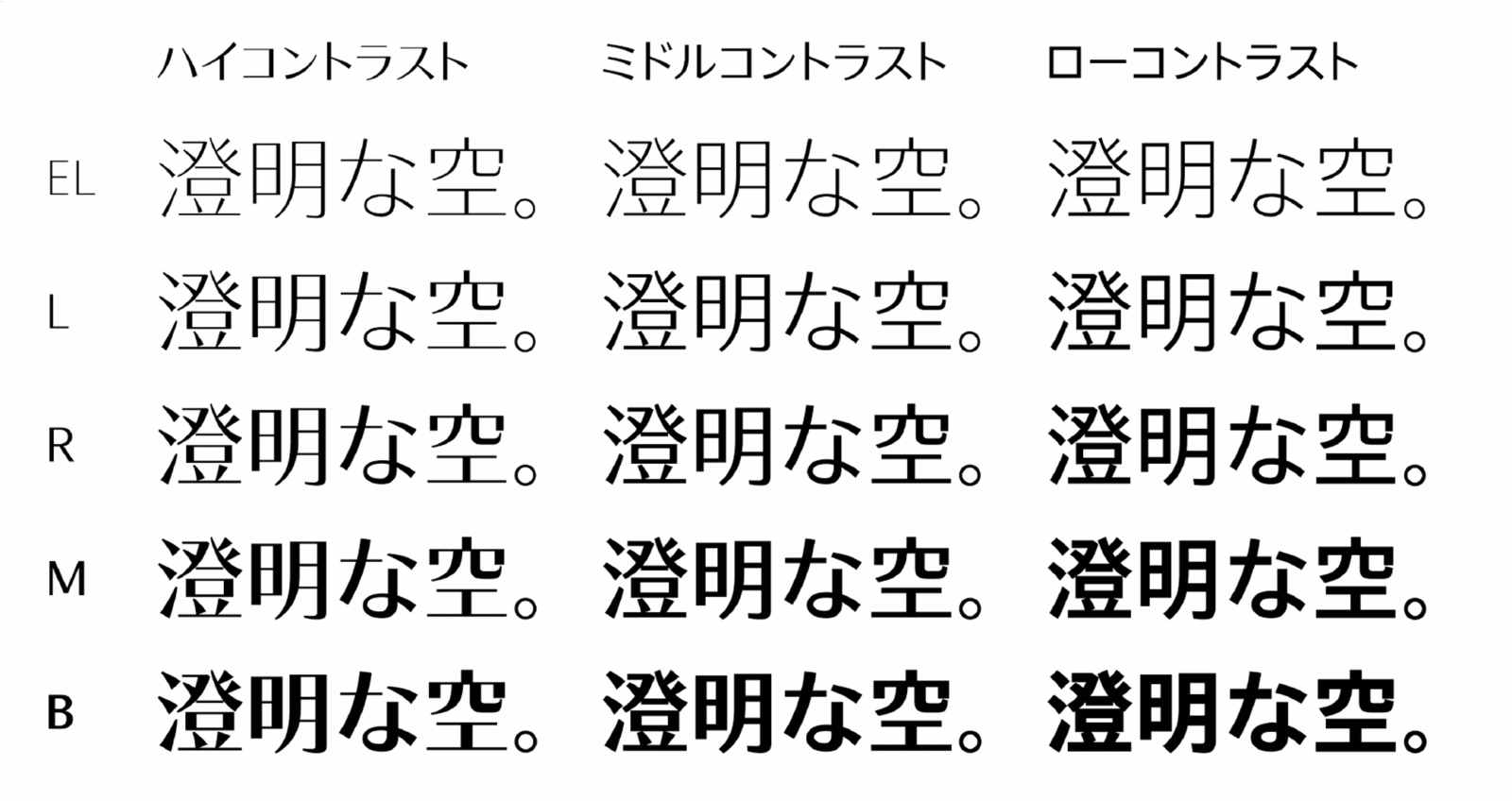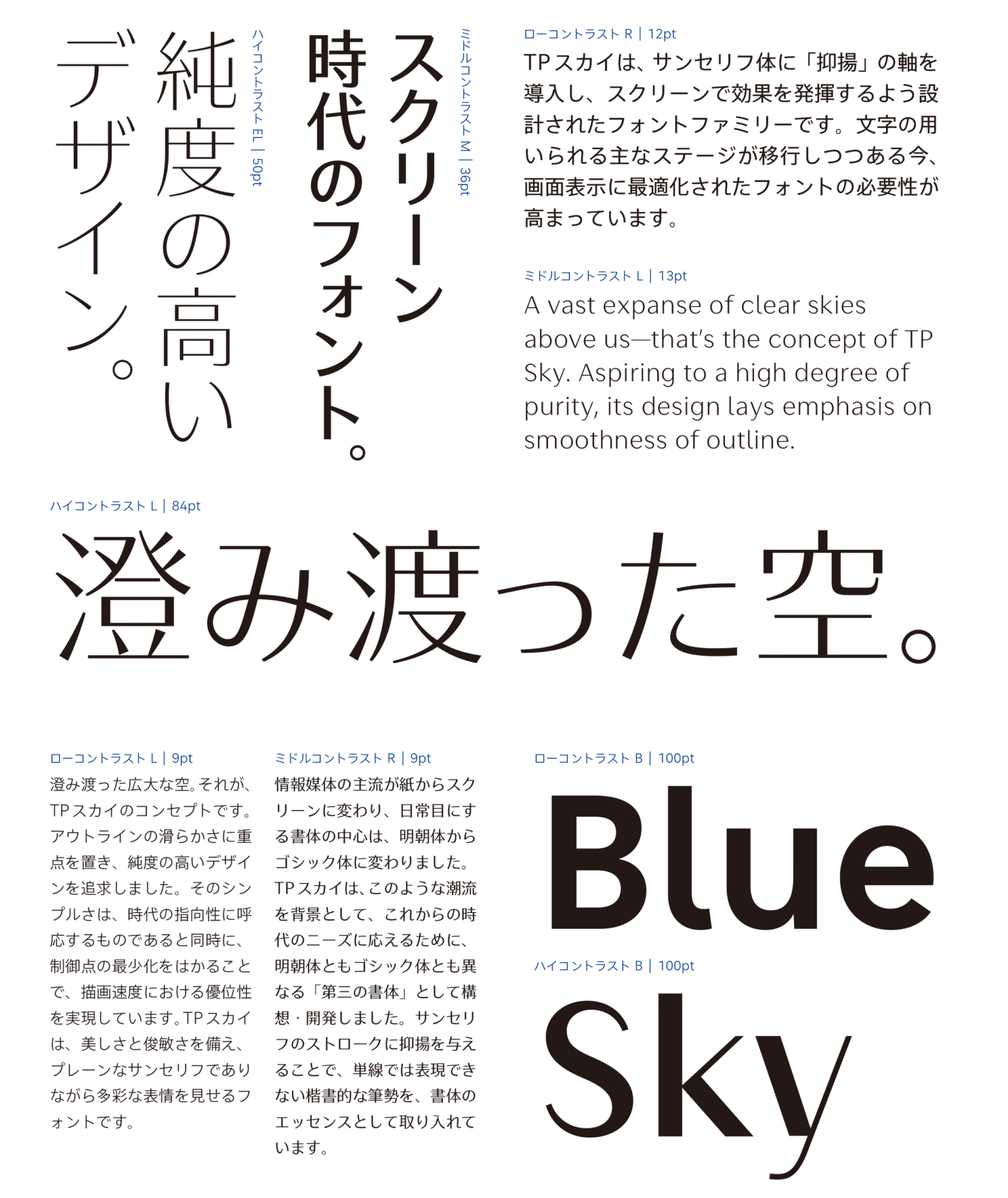
タイププロジェクト、スクリーン表示に最適な新フォント 「TP スカイ」を発表
サンセリフ体のストロークに抑揚を与えたクリアなデザイン
タイププロジェクト株式会社 (東京都練馬区 代表取締役社長 鈴木 功、以下 タイププロジェクト) は、スクリーン時代の多様な要求に応えるサンセリフフォント「TPスカイ」を発表しました。澄み渡った広大な空をコンセプトにした TPスカイファミリーは、本日より発売を開始いたします。
TP スカイは、サンセリフ体のストロークに抑揚を与え、単線では表現できない楷書的な筆勢を取り入れた書体です。アウトラインの滑らかさに重点を置き、簡潔な文字描画によってフォントデータの軽量化をはかり、明快な文字表現で表示適性を高めました。
タイププロジェクトの代表取締役 鈴木 功は、「媒体が紙からスクリーンへと変わり、数百年続いた第一書体の座が明朝体からゴシック体に移りました。スクリーン上の出来事とはいえ、この現象は非常にラディカルなものといえます。私たちは、明朝体・ゴシック体に続く『第三の書体』として、TPスカイを開発しました。スクリーン用途で重視されるフォントの機能的な課題と、簡潔明瞭なフォントが好まれている時代の審美的な要求に応えることができると自負しています」と述べています。
TP スカイは、文字情報をあつかう上で重要な5つのウエイト (エクストラライト、ライト、レギュラー、ミディアム、ボールド) と、判読性の向上に有用な3つのコントラスト (ハイ、ミドル、ロー) を備えています。
TPスカイは、本文と見出しやタイトルとキャプションなど、表示サイズや解像度に最適なフォントを選択することで、明朝体とゴシック体を用いることなく、高いレベルでの画面の統一感を実現します。ハイコントラストは、明朝体のニュアンスを残しながらもより簡潔で透明感のあるフォントです。また、ミドルコントラストは、可読性の高さと共に、勢いのあるストロークの抑揚が画面に精彩を与えます。ローコントラストは、文字の黒みを揃えることで読字の安定性を高め、フラットでプレーンな UI に最適なフォントです。